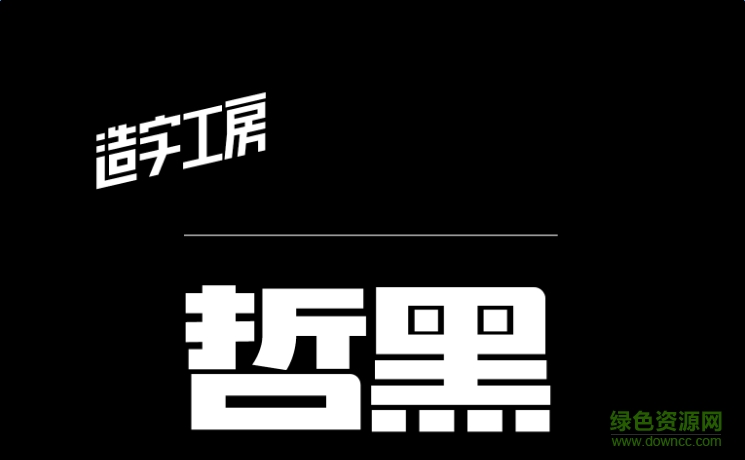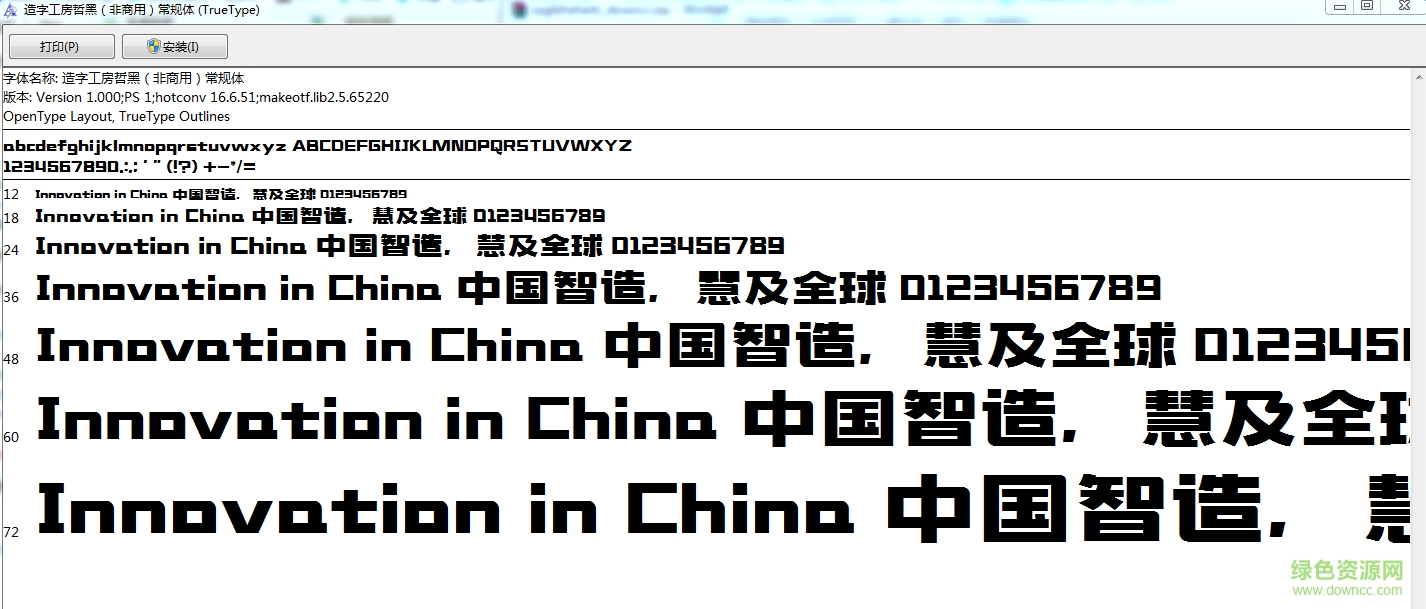
造字工房哲黑體是一款造字工房類穩(wěn)重黑風(fēng)格字體軟件,哲黑體整體效果得體大方,在個性文章以及海報標題設(shè)計方面有著不錯的應(yīng)用,非常的醒目,還有更多好看字體盡情期待,歡迎到綠色資源網(wǎng)下載體驗!
造字工房哲黑體結(jié)構(gòu)明朗、字形端正、筆畫橫平豎直,字形整體風(fēng)格剛勁有力,其筆畫古樸沉厚又不失沉穩(wěn)之風(fēng)。適用于大標題及個性品牌設(shè)計推廣等環(huán)境。